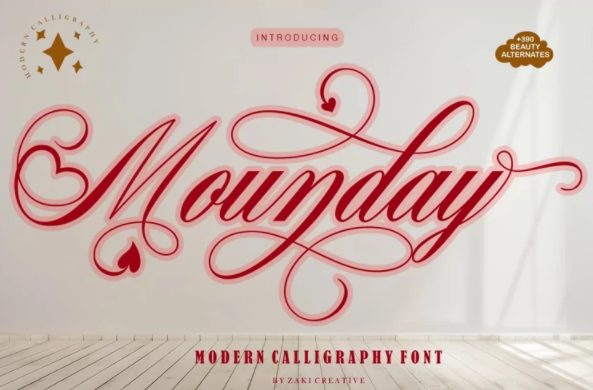
[Fontbundles] Mounday Font (2021)
Представляю свой новый продукт под названием Mounday | Calligraphy Script.
Шрифт Mounday включает в себя прописные и строчные буквы, цифры, большое количество знаков препинания и лигатур. Все строчные буквы включают завершающие штрихи и альтернативный шрифт.